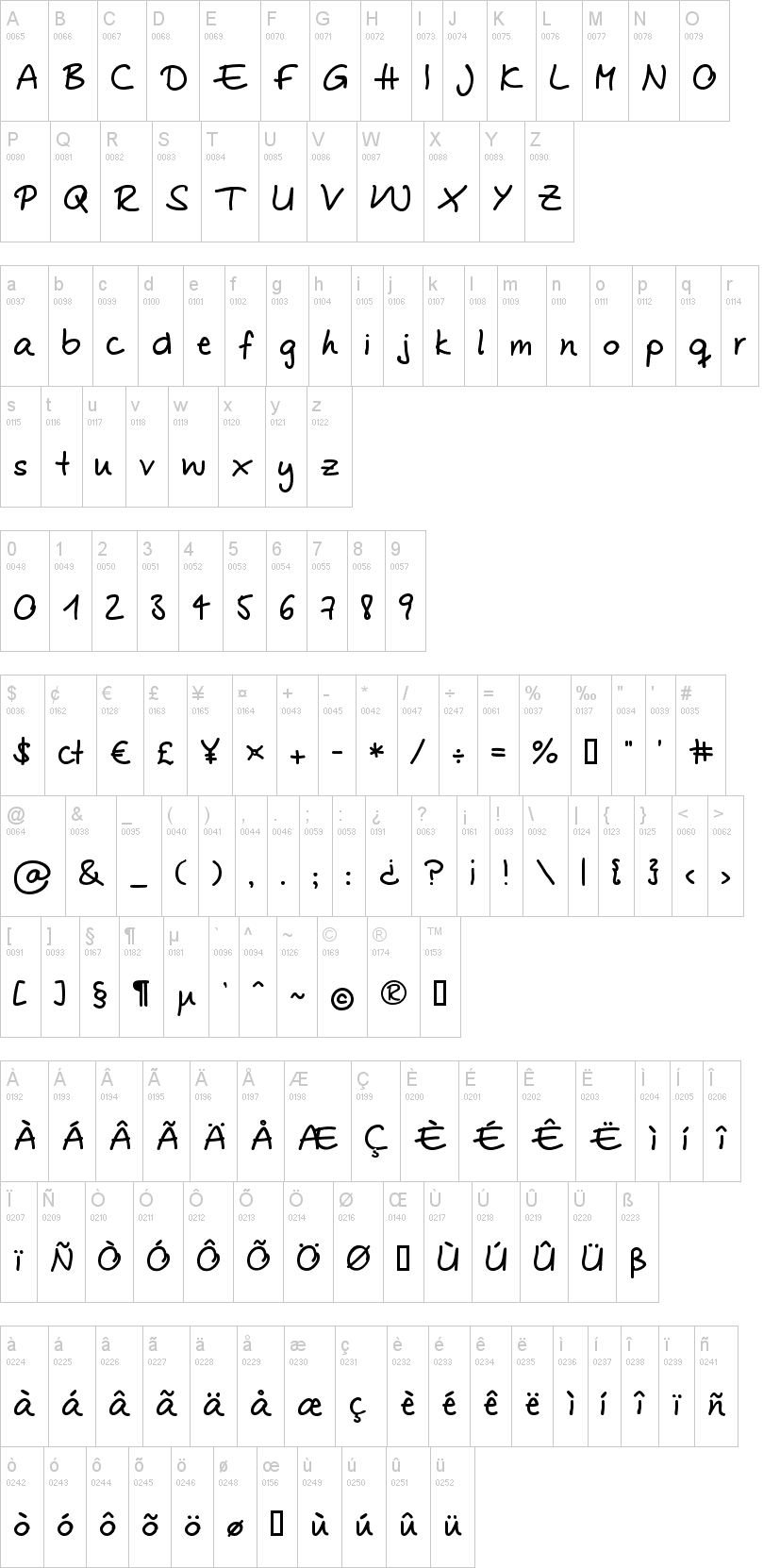
Mareen's Print
Mareen's Print 是一款漂亮的手写字体,它具有细腻的笔画和柔和的曲线。字体的外观自然可爱,可以用于设计海报、招贴、卡片、商标等。它具有良好的可读性,可以轻松阅读,而且可以轻松传达信息。它还具有多种字母和符号,可以满足不同的设计需求。
Mareen's Print是一款非常不错的手写艺术字体,具有很好的视觉感,适合于文化类的宣传设计、商业类品牌的广告和产品包装设计以及个性化文字排版等较多场景。
Mareen's Print字符映射图